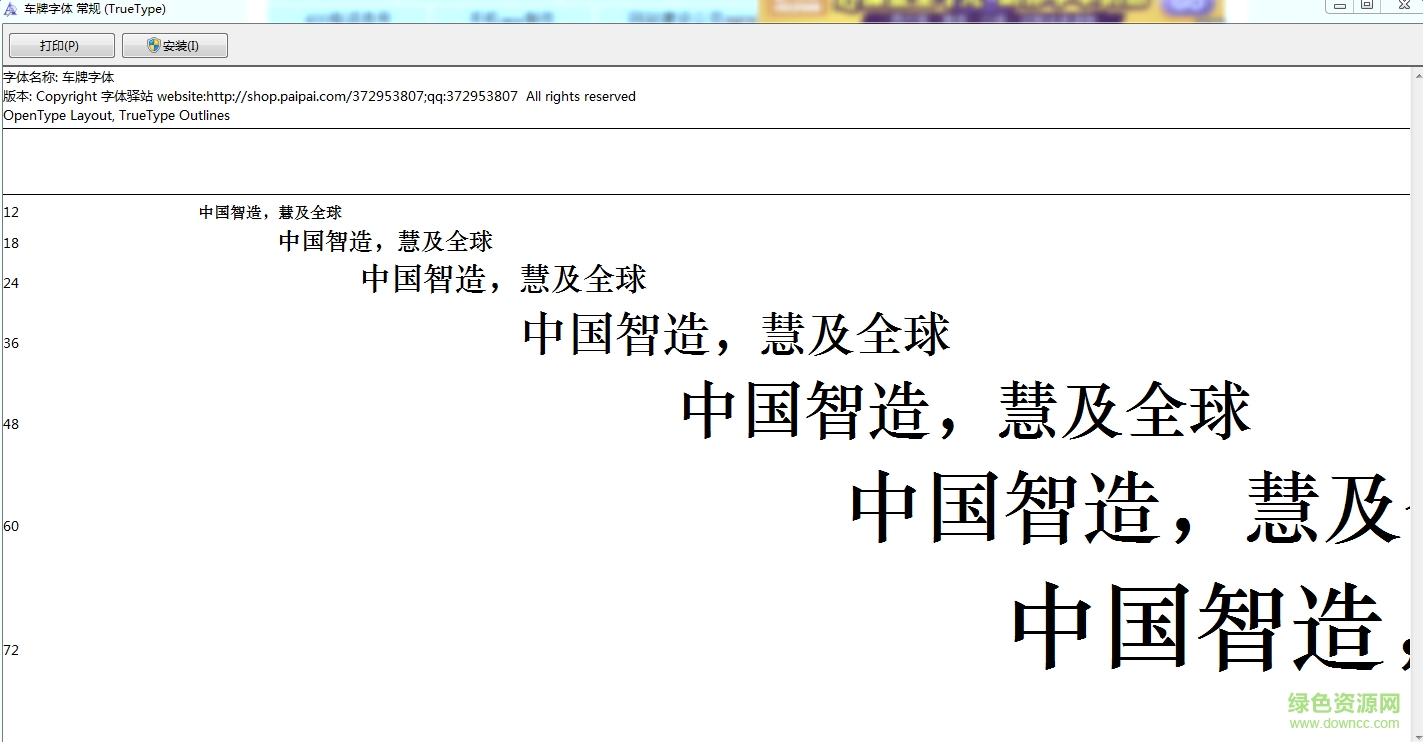
中國汽車車牌字體是一款結(jié)合了黑體和宋體改造上的車牌專用字體,字庫完整,該字體具有一定的特殊性,只有在專門的設(shè)備上才能輸出,有需要者歡迎在綠色資源網(wǎng)下載!
車牌字體為最大限度上防止偽造車牌,公安部為現(xiàn)行車牌開發(fā)了一種特殊字體,以黑體為基本字體進行了一定的改進,使得目前通用的電腦上的任何字體都不與其完全吻合,只在公安交警部門或指定的車牌制作單位的輸出設(shè)備上可以輸出。